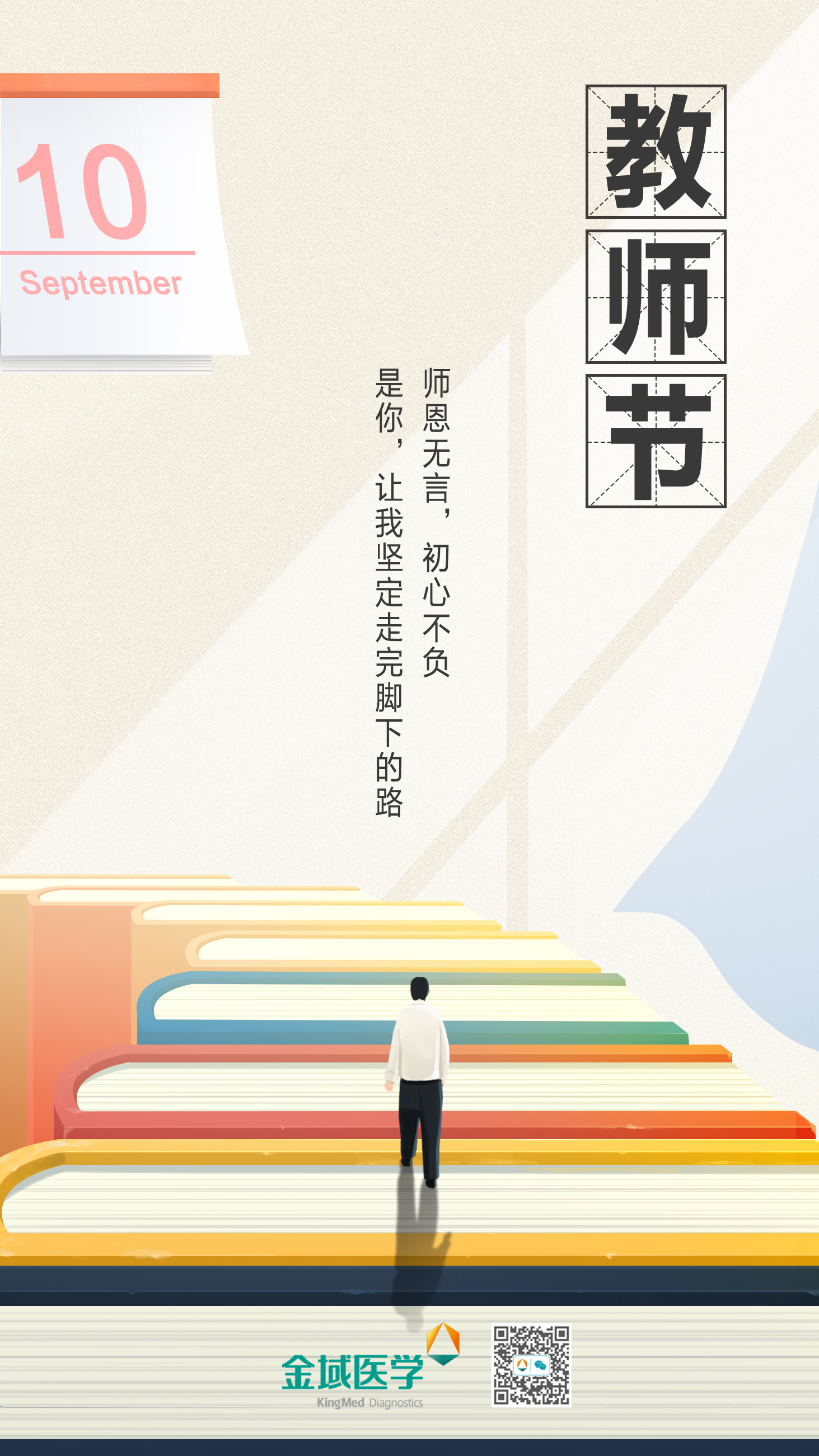
中国人方正字,中国属于世界的,而世界也是中国的。方正兰亭黑Pro Global家族字体是方正字库的第一款全球字库,目前发布的第一个版本拥有八个字重,支持语言达到了200多种语言,包含中文,拉丁文,西里尔文,希腊文,阿拉伯文。该字体为数字媒体的跨平台应用带来更优秀的体验,是方正字库与国际字库厂商合作的一次有益尝试。